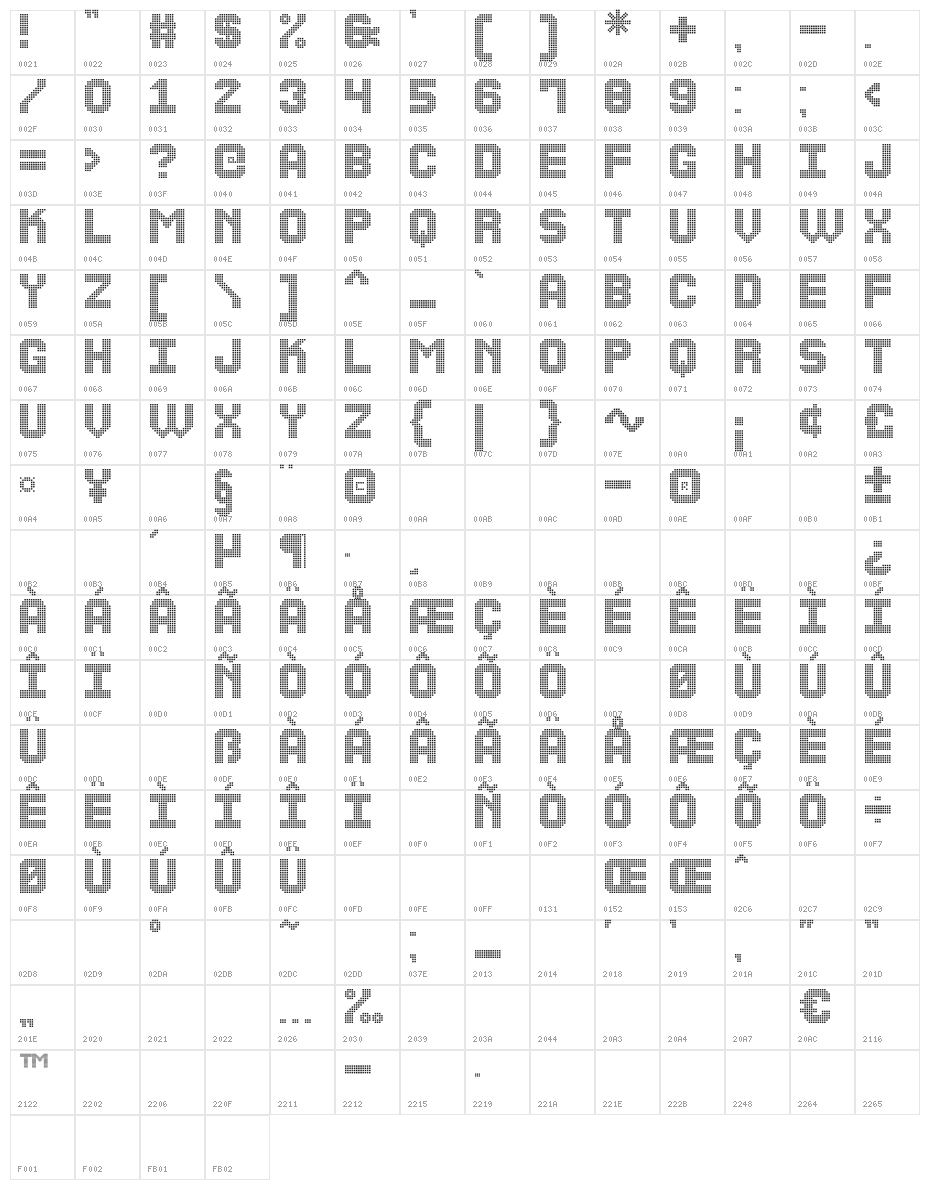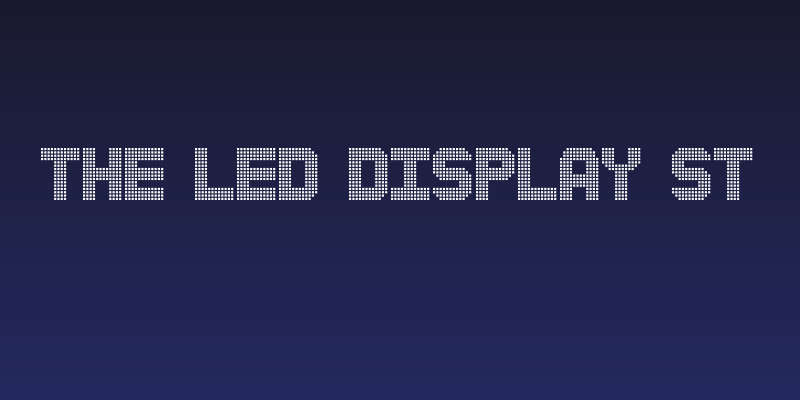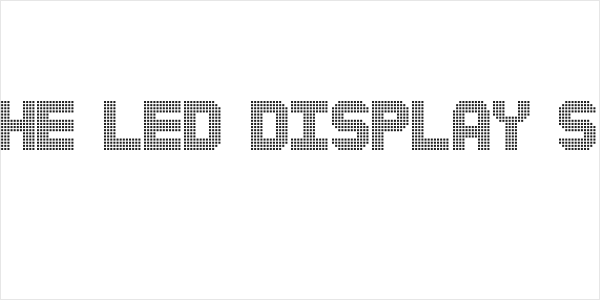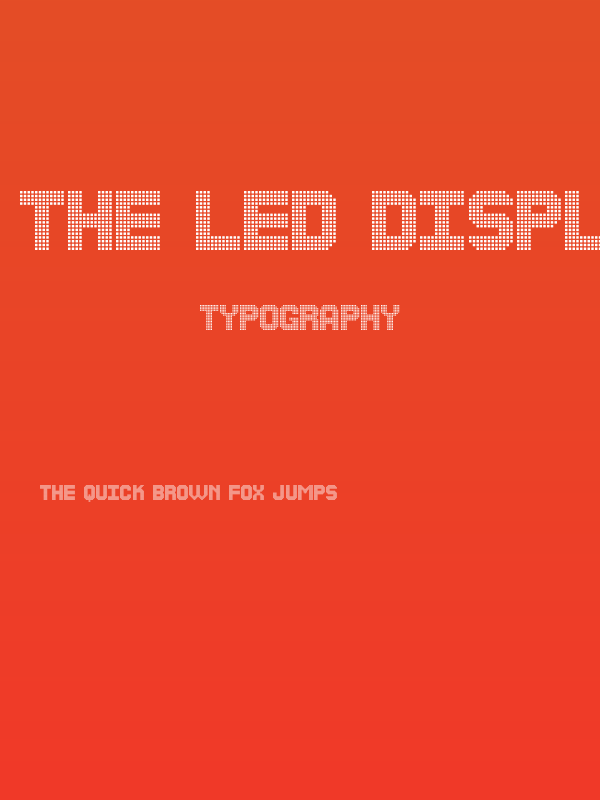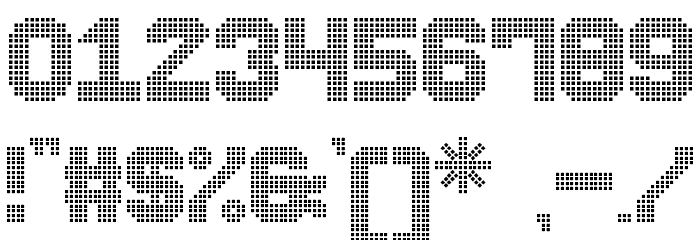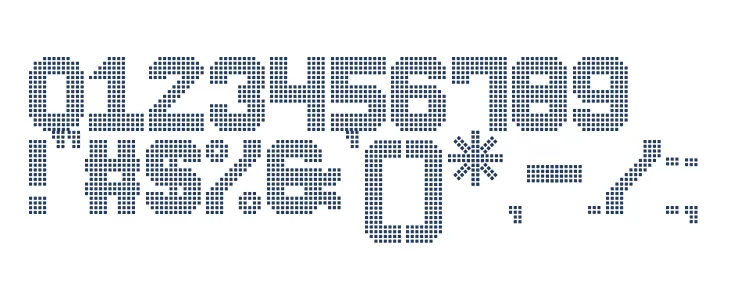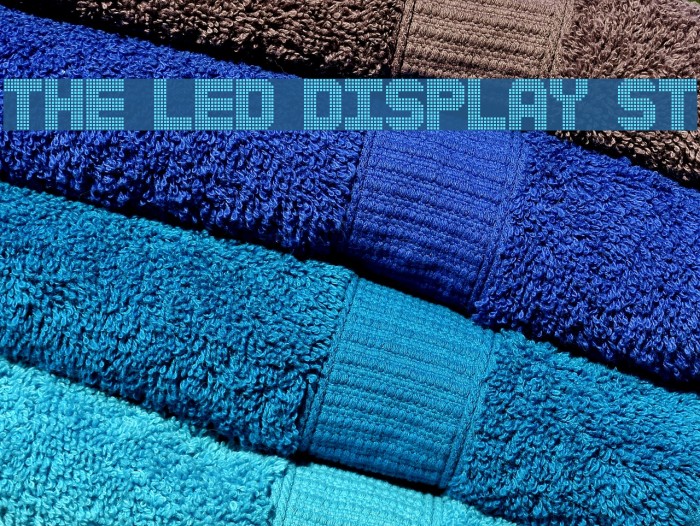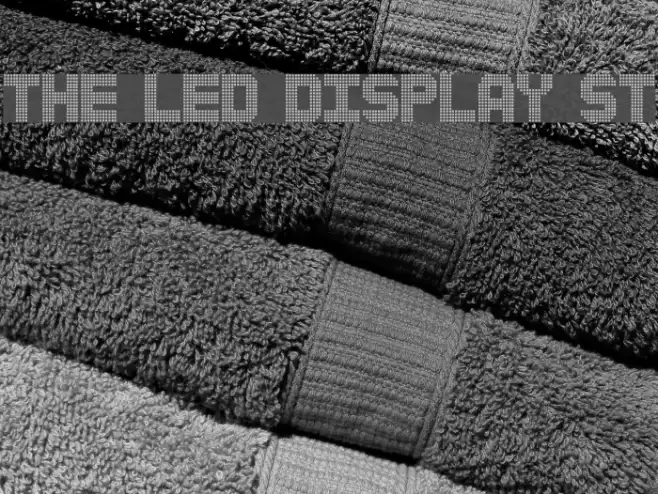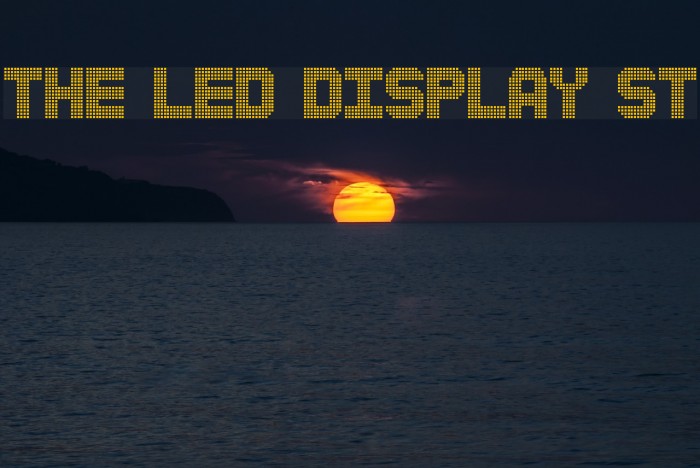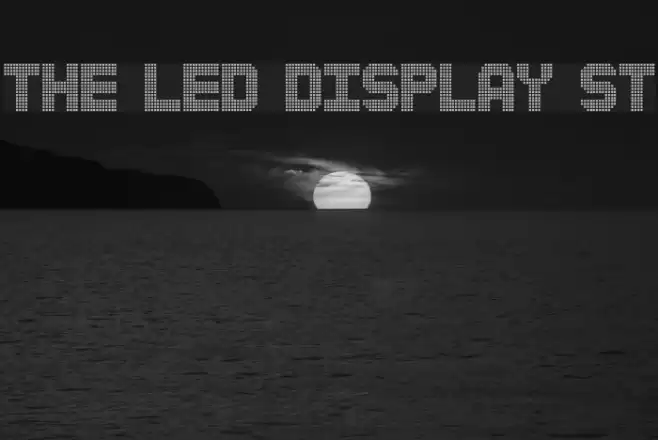
The Led Display St Font
| Caso de uso | Headlines, Digital displays, Tech-themed projects |
| Proyectos propuestos | Ideal for digital displays, tech-themed designs, electronic signage, and modern branding projects. |